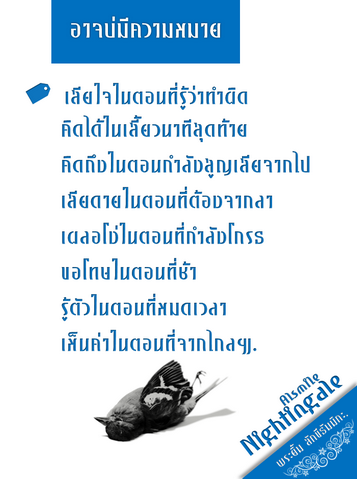
ก็รอฟังความสนใจเหมือนกันครับ
ตั้งใจว่าปีนี้จะเริ่มปล่อย ๆ มาให้ใช้กันได้บ้าง
ขอพิจารณาจากความสนใจของบุคคลส่วนใหญ่ในที่นี้ก่อน
ถ้าเขาไม่สนใจ เราก็ไม่กล้าแจก เพราะสวยในสายตาเรา แต่เขาอาจไม่ชอบก็เป็นได้
จะเริ่มปล่อยในอีกไม่นานนี้ครับ
เทอมนี้เรียนหนักพอสมควร แต่เจียดเวลามาทำตามความชอบใจนิดหน่อย
เคยทำแล้วก็ทำ ๆ ไป สักพักจะรู้สไตล์ตนเองแล้ว
คิดจะขอความรู้เรื่องทำฟอนต์สไตล์อัศจรรย์ของ อ.เลย์ เหมือนกัน
แต่รอเวลา สักนิดครับ
ลองเสนอมาว่าสนใจฟอนต์ไหน หลวงพี่จะปรับแล้วค่อย ๆ ปล่อยมาให้ใช้ครับ
อยากว่าแต่ถามชื่อฟอนต์ของหลวงพี่เลยฮะ
..ถามแค่ว่าหลวงพี่นำออกมาให้ยลกี่ฟอนต์แล้ว ?
ผมว่าเรื่องแจก ไม่แจก หลวงพี่นำความสนใจของคนที่นี่ หรือคนข้างนอก มากำหนดไม่ได้หรอกครับ
อยู่ที่เจตนาว่าเราทำออกมาทำไมมากกว่า อยากแจกก็แจก ไม่อยากแจกก็ไม่ต้องแจก ตามความสบายใจครับ
(ผมเองก็มีฟอนต์ทำเล่นๆ ไม่ได้ปล่อยหลายตัวไป ไว้ใช้ในกรณีที่อยากใช้แค่นั้นเอง)
งาน Type Design เป็นงานที่ไม่สามารถกำหนดได้ว่าผู้ใช้จะเอาไปใช้แนวไหน ใช้กับอะไร จะมีการใช้ประหลาดแค่ไหน
แม้ว่าตอนสร้างเราจะตอบตัวเองได้ว่าสร้างขึ้นมาทำไม ใช้กับอะไรก็ตาม
เห็นฟอนต์ตัวเองในงานหลากหลายประเภท ทั้งที่คาดถึง และคาดไม่ถึง สนุกดีออกครับ
ผมไม่เคยคิดว่าใครจะมาชอบฟอนต์ผมเลยนะครับ ผมทำเพราะผมอยากใช้
ทำเสร็จก็แจก แน่นอนตอนแจกก็ไม่ได้ผ่านการทดสอบเท่าที่ควร
บางอยากเพิ่งมาเห็นเมื่อผ่านเวลาไปเป็นเดือนเป็นปี
แล้วเราค่อยมาตามแก้ (ถ้าอยากแก้)
ของฟรีไม่ค่อยมีใครด่าหรอกครับ มีแค่คนชม
เห็นควรด้วยกับพี่ๆ หลายคนครับ
สนุกก็ทำครับ อย่าไปมัวไปมองว่าใครจะชอบหรือไม่ชอบ
ผมว่า ความคิดของแต่ละคนไม่เหมือนกัน ใครชมเราก็ยินดี ใครไม่ชมหรือตำหนิ เราก็เอาสิ่งนั้นมาปรับใช้แก้ต่อไปในภายหลังก็ได้นี่ครับ  :12:
เห็นด้วยครับ ถ้าอยากรู้ว่าคนจะสนใจไหม ก็ต้องลองสักจึ้กครับ
แล้วฟีดแบ็กจากทั่วสารทิศจะมาเอง ไม่ใช่แค่คนหลักสิบหลักร้อยที่นี่
กำลังพิจารณาฟอนต์ว่าจะปล่อยตัวไหน อาจารย์ก็สั่งงานเพิ่มซะงั้น เฮ่อ...
พิมพ์เล่น ๆ ฟอนต์นี้ยังแก้ปัญหาสระอือหายไม่ได้
ถ้าขนาดต่ำกว่า 24 ลงไปสระอือจะหายไป
ทำด้วยสัมมาสังกัปปะ ออกมาได้แบบนี้
ยังไม่พอใจ คิดว่าจะทำจนกว่าจะพอใจให้ครบ ในรูปที่ปรารถนา :52:
ยังทำไม่ครบชุดนี้
เดี๋ยวหาเวลาทำให้ครบก่อนนะ จะเอาลงมาให้ดูเรื่อย ๆ...
ยังไม่ครบ ค่อย ๆ ทำไปเรื่อย ๆ
อันนี้น่าจะเรียกว่าฟอนต์ได้ ทีแรกทำเล่น ๆ ตอนนี้คิดว่าน่าจะทำจริง ๆ
ลองปรับใหม่ ใส่เลขไทย
คิดว่าน่าจะเป็นฟอนต์ได้อีกไม่นานนนนนนนนนน......
อันนี้สวยมากกกกกกกกกกกก ตลาดก็ต้องการมากๆๆๆๆๆๆ ด้วย
สอดคล้องกับตัวโรมัน เห็นนิยมในวงการแพคเกจจิ้งอาหารมากๆ